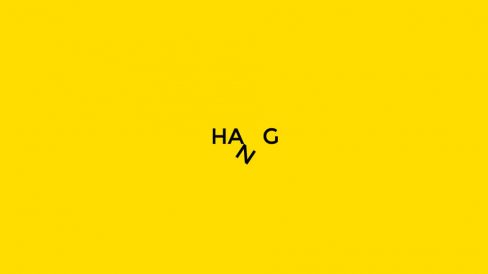
Projeto brinca com tipografia de palavras para revelar seus significados
Criado pelo designer Arun Raj, Tipography Word Play poderia auxiliar muitas pessoas no aprendizado do inglês
Não tem muito tempo que mostramos por aqui o Chineasy, projeto da designer ShaoLan que facilita o aprendizado do mandarim com um sistema visual que usa os ideogramas originais como base para uma ilustração que revela seu significado. É provável que facilitar o aprendizado do idioma inglês não tenha sido o principal objetivo do designer indiano Arun Raj, mas é impossível não enxergar esta possibilidade no projeto Tipography Word Play.
De um jeito bem minimalista, Raj cria representações gráficas do significado de cada palavra, usando a tipografia de cada uma. Por exemplo: o T de death vira uma cruz sobre um fundo preto, criando uma rápida associação com a morte. O P de jump aparece um pouco acima do restante das letras, como se realmente estivesse pulando. Já o T de helicopter é uma hélice, enquanto as duas letras O de baloon estão flutuando.
É tudo muito bem pensado e certamente poderia ser aplicado em diversos idiomas, como forma de ampliar o vocabulário.
O projeto pessoal é executado sempre que sobra um tempo para o designer, então vale ficar de olho para novas atualizações. Em seu portfolio no Behance é possível conferir todas as palavras, além de outros trabalhos assinados por ele.